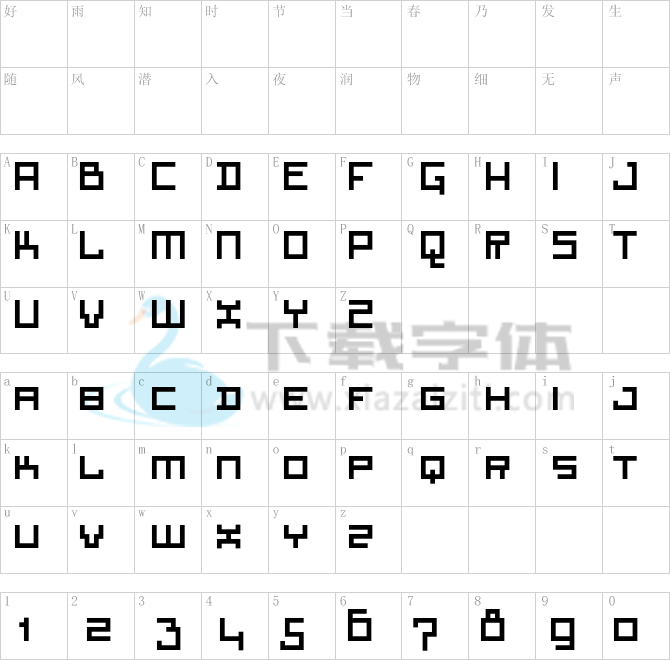
Aquarius Small Caps.otf字体下载,这款字体结构工整、笔画清晰,兼顾美观与易读性,适用于标题、正文、海报、包装、LOGO 等多种场景。字形优雅稳定,风格百搭耐看,适配日常排版与创意设计,让文字呈现更舒适、更具质感。Aquarius Small Caps.otf字体下载一笔一画,皆是细节,以均衡的比例、流畅的线条打造舒适视觉体验,字形端正大气,风格简约现代。无论是商业设计、品牌宣传还是日常排版,都能轻松驾驭,让文字更有格调与力量。Aquarius Small Caps.otf字体下载字体下载。